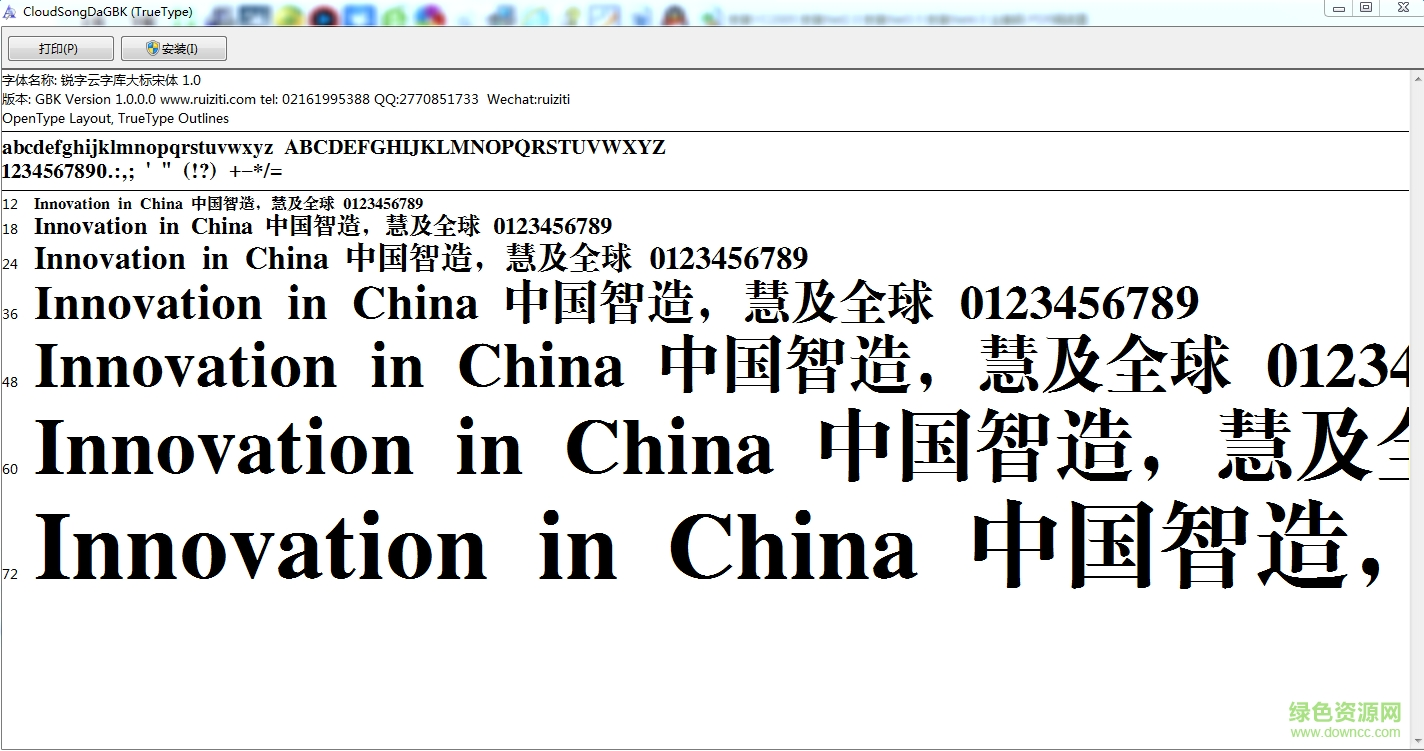
cloudsongdagbk字體是一款古色古香的銳字工房云字庫大標宋體gbk,字形端正清秀,勻稱美觀,表現(xiàn)力強,十分實用,適合正文標題設計,歡迎大家免費下載!
1.筆畫有粗細變化,是橫細豎粗;
2.末端有裝飾部分(即“字腳”或“襯線”),點、撇、捺、鉤等筆畫有尖端;
3.特點是橫輕豎重,結構均勻,筆法嚴謹,橫線尾和直線頭呈三角狀;
4.字形端正、剛勁有力,有老宋體和黑體兩者結合的特點。